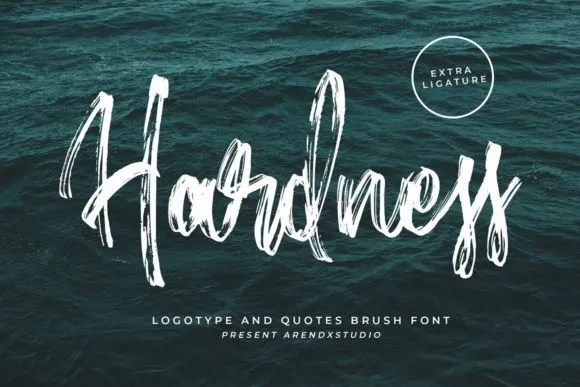
Hardness Font – Download Grátis
A Hardness Font é uma tipografia de script feito à mão que transmite naturalidade e tendências atuais. Esta fonte está projetada pelo arendxstudio e pode ser encontrada no 99designs, adaptando-se perfeitamente para um leque amplo de projetos. Suas linhas ágeis e expressivas são a escolha ideal para trabalhos que precisam de uma mão humana, como criação de marcas, identidade visual, design de casamentos, postagens de mídia social, anúncios, embalagens de produtos, designs de produtos, etiquetas, fotografias e até mesmo marcadores de água. Ideal tanto para personalizar seu logotipo quanto para adicionar um toque autêntico a qualquer projeto visual. Com Hardness Font, seus projetos certamente brilharão ainda mais.